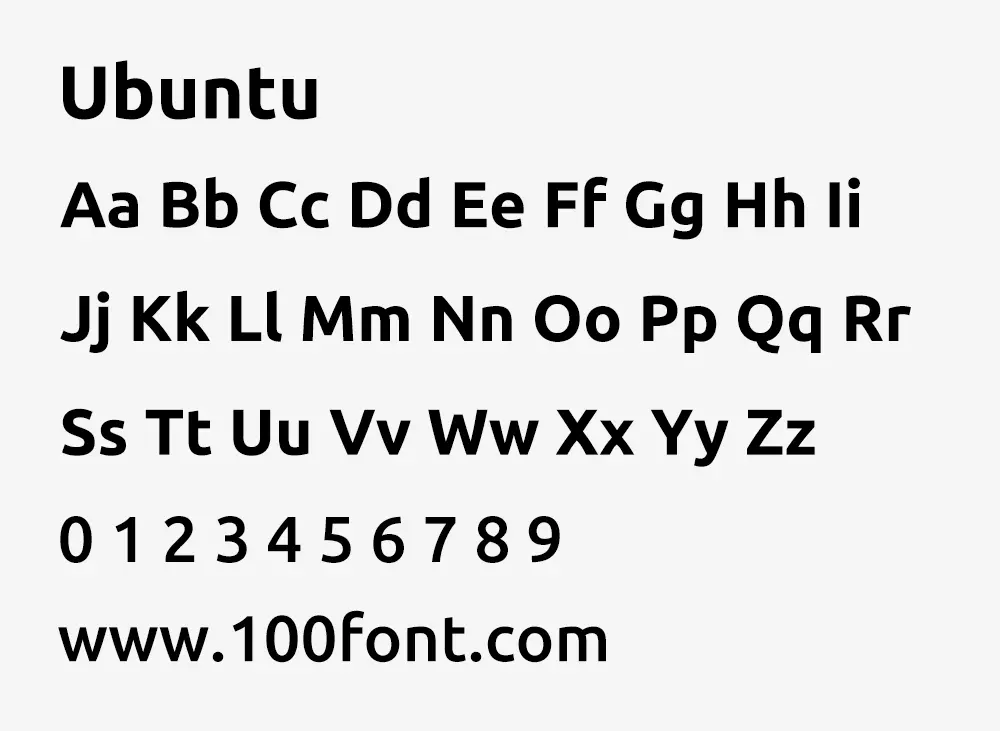
Ubuntu字體是專門為補充Ubuntu的語調而創建的。它具有現代風格,包含Ubuntu品牌特有的特點,傳達了精確、可靠和自由的態度。
關於Ubuntu字體家族:Ubuntu字體家族是一組匹配的新libre/open字體。該開發由Canonical代表更廣泛的自由軟件社區和Ubuntu項目提供資金。字體技術設計工作和實施由Dalton Maag負責。
最終的字體Truetype/OpenType文件和用於生產字體系列的設計文件都是在開放許可證下分發的,我們明確鼓勵您進行實驗、修改、共享和改進。字體為無襯線字體,使用OpenType功能,並在桌面和移動計算屏幕上手動提示以保持清晰。
Ubuntu字體家族的範圍包括世界各地Ubuntu用戶使用的所有語言,這符合Ubuntu的理念,即每個用戶都應該能夠以自己選擇的語言使用軟件。因此,Ubuntu字體家族項目將擴展到更多的書面語言。
事實和數字:Ubuntu字體家族是一個有22種風格的無襯線字體家族,加上一個重量和寬度軸可調的可變字體。它的固定寬度配套產品UbuntuMono有8種風格和可變字體,重量軸可調。
The Ubuntu typeface has been specially created to complement the Ubuntu tone of voice. It has a contemporary style and contains characteristics unique to the Ubuntu brand that convey a precise, reliable and free attitude.
About the Ubuntu font family
The Ubuntu font family are a set of matching new libre/open fonts. The development is being funded by Canonical on behalf the wider Free Software community and the Ubuntu project. The technical font design work and implementation is being undertaken by Dalton Maag.
Both the final font Truetype/OpenType files and the design files used to produce the font family are distributed under an open licence and you are expressly encouraged to experiment, modify, share and improve. The typeface is sans-serif, uses OpenType features and is manually hinted for clarity on desktop and mobile computing screens.
The scope of the Ubuntu Font Family includes all the languages used by the various Ubuntu users around the world in tune with Ubuntu's philosophy which states that every user should be able to use their software in the language of their choice. So the Ubuntu Font Family project will be extended to cover many more written languages.
Facts and figures
The Ubuntu font family is a sans-serif typeface family available in 22 styles plus a variable font with adjustable weight and width axes. . Its fixed-width companion, Ubuntu Mono, comes in 8 styles and a variable font with an adjustable weight axis.